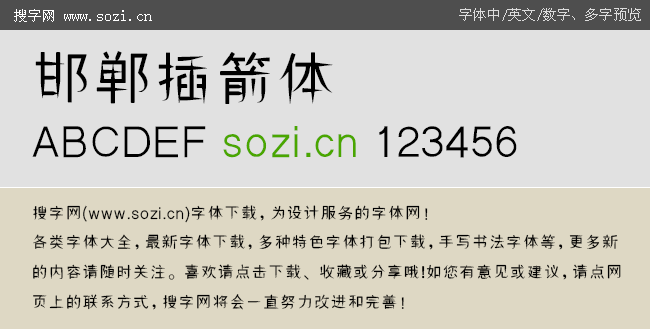
邯鄲插箭體
搜字網(wǎng)提供一款邯鄲插箭體中文藝術(shù)字體下載,邯鄲插箭體是一款一款非常有趣的藝術(shù)字體。由黑體字為原形進(jìn)行藝術(shù)設(shè)計(jì),筆畫像箭頭一樣尖利,整體效果十分出色。可用于藝術(shù)設(shè)計(jì)、包裝印刷、圖形設(shè)計(jì)等領(lǐng)域。